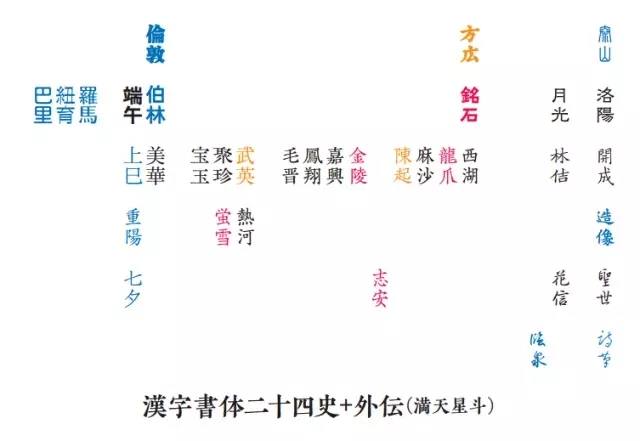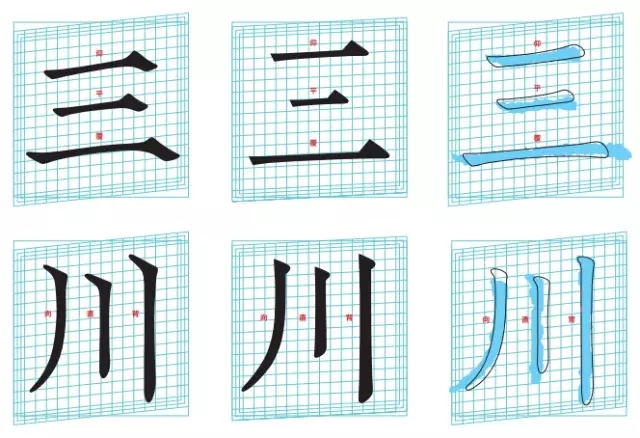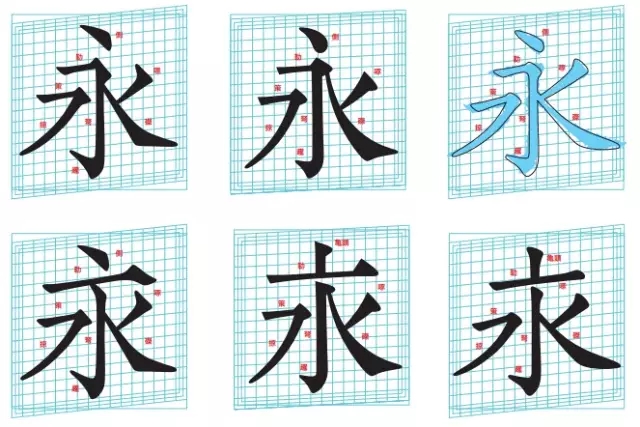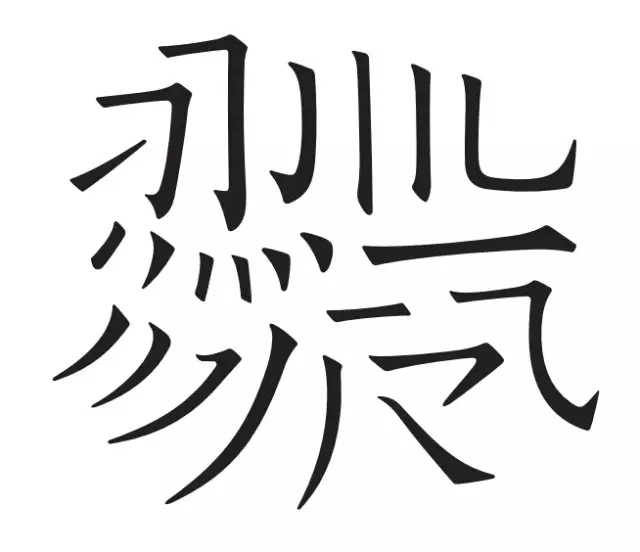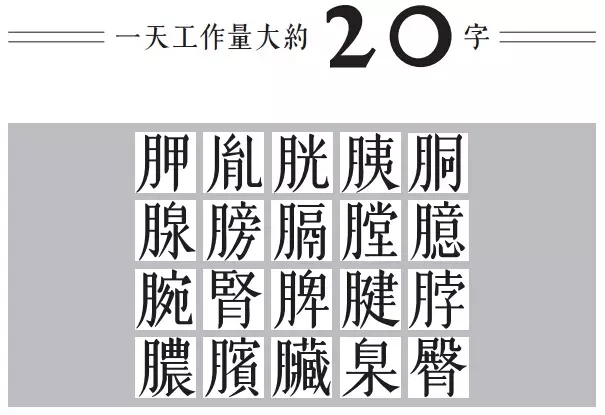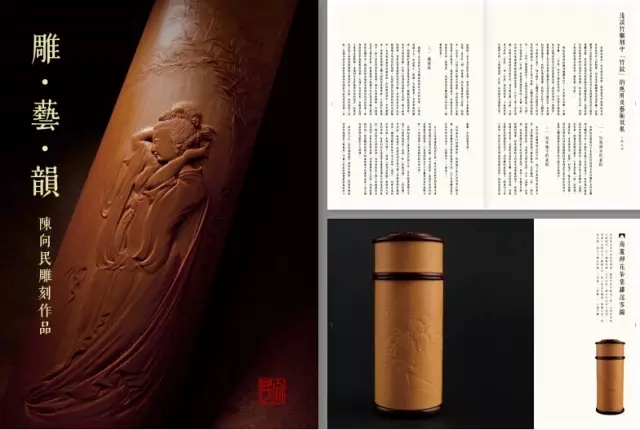
中文复刻字体研讨会
导语海报设计:杨林青1月9日下午2时,一场由北京北大方正电子有限公司(以下简称“方正电子”)与北京大学现代出版研究所合作主办的字体盛会——“中文复刻字体研讨会暨方正金陵粗、方正金陵细、方正龙爪、方正萤雪字体发布会”在北京大学百年纪念大讲堂隆重召开。300余名字体及设计爱好者齐聚一堂,与在场的对古籍文化和字体颇有研究的大咖们一起,近距离探讨了复刻字体的前世今生以及未来,并一同见证了方正金陵粗、方正金陵细、方正...
1月9日下午2时,一场由北京北大方正电子有限公司(以下简称“方正电子”)与北京大学现代出版研究所合作主办的字体盛会——“中文复刻字体研讨会暨方正金陵粗、方正金陵细、方正龙爪、方正萤雪字体发布会”在北京大学百年纪念大讲堂隆重召开。
300余名字体及设计爱好者齐聚一堂,与在场的对古籍文化和字体颇有研究的大咖们一起,近距离探讨了复刻字体的前世今生以及未来,并一同见证了方正金陵粗、方正金陵细、方正龙爪、方正萤雪四款复刻字体的发布。
以下是来自七位嘉宾(肖东发、今田欣一、汤婷、应永会、刘庆、姜寻、杨林青)以及学术主持仇寅的精彩分享,满满的都是干货哦~
主题演讲环节
肖东发
北京大学新闻与传播学院教授、北京大学现代出版研究所所长
演讲主题:《朝阳产业探寻规律——从出版史说起》
有人说出版是夕阳产业,我不赞成这个观点,如今我们讲的是大出版,它一定是个朝阳产业。因为有教育就得有出版,社会各行的发展,跟出版是互动前行的,只要人类存在,有信息传播,就有出版。回顾出版史我们不难得出很多有意义的结论。出版史有两个基础,其一就是文字要有语言为基础,因为文字是记录语言和传播的符号;其二,文字产生的基础是实物,没有实物也是不可能产生文字的。有文字的历史就是人类的文明史,这是第一个大的飞跃。再有一个飞跃,我觉得就是计算机光电技术。人类信息传播是一个动态的过程,从无到有,从简到繁,而科学技术的发展是整个推动力。为什么纸以前的媒介的都被淘汰了?我认为中外所有媒介的优势纸都具备,它又克服掉了它们的缺点。有人预言,未来是无纸的社会、计算机能够完全取代纸。我认为不可能,因为计算机不具备压倒优势,纸不受地方限制,我认为,纸永远不会消亡。为什么说出版是永远的?我的结论,出版是永恒的朝阳产业,它不仅是一个产业,它还有特殊的文化属性,关系到人类灵魂的升华。传统出版也不会消亡,就像纸业不会消亡一样。人们不能光网上看书,这叫浅阅读、快阅读,要想慢阅读、深阅读还得看书本。当然它俩不是矛盾的,新技术给出版如虎添翼;此外,不管是传统出版还是数字出版都离不开字体。我最后的结论是,理想和责任是出版人永远不变的人文情怀,融合与创新是出版永远的主旋律。
今田欣一
日本著名字体设计师、欣喜堂字体公司负责人
演讲主题:《温故知新》
2012年和方正电子一起合作的金陵、龙爪和萤雪终于可以发布了。现在我给大家展示一下“汉字书体二十四史+外传”,日语的书体就是字体,黑色的、橘色的和红色的加起来就是二十四史,蓝色的没有放到“二十四史”里面,只做了一些实验,所以补在后面,叫“外传”(满天星斗)。
右边这一块主要是手写系的字体。最右边一列是以石碑文字为基础做出来的,从上到下分别是篆书、隶书、楷书、北魏的石碑、行书和草书,出自《熹平石经》的洛阳、出自《开成石经》的开成,出自王羲之行书的圣世,出自怀素草书的诗草。第二列是从刊本选出来的,隶书体的月光、楷书体的林佶和行书体的花信。底下的叫临泉,是日本特有的。左边的端午、上巳、重阳、七夕是现代排印的活字字体,分别是黑体、宋体、楷书和仿宋,端午是从人民文学出版社的字样中抠出来做的,上巳是从商务印书馆的刊物中抠出来的,重阳是汉文正楷书局的,七夕则是中华书局,这四款是从中国的出版社做的中国活字中复刻出来的。从最右边的书法手写体到左边的印刷字体,中间的这部分是我所研究的“二十四史”的最关键的一个系列。我给它们分成了几个区,我给每个区起的名字可能和中国朋友起的名字不一样。西湖、龙爪、麻沙、陈起是宋朝体,志安是元朝体,金陵、嘉兴、凤翔、毛晋是明朝体,热河、萤雪是从清朝刻本出来的,我管它们叫清朝体,武英、聚珍、宝玉是过渡期明朝体,美华是近代明朝体。
接下来要说说这些刻本字体,我是怎么选的。北宋刻本,完全继承了唐朝的风格,保留的非常多,到了南宋以后,印刷的三大出版地是浙江、四川和福建,所以我在复刻宋朝字体的时候主要是从三大刻本出版地里找的。龙爪,我是选的四川刻本做出来的,方正龙爪体的原形就在这里。麻沙是福建刻本的字体,据说福建刻本是以柳公权的笔法为主。西湖、陈起是浙江刻本。志安是元朝体,它的书体风格和赵孟頫的笔法是很接近的。在复刻明朝体的时候,我是按出版社来选的刻本,金陵出自南京的国子监,嘉兴是佛教的刻本,凤翔选的是《乐律全书》郑藩刻本,毛晋选自非常有名的《毛晋汲古阁》刊本,它书法的笔法保留的比较多。后面的清朝刻本字体,是怎么选的呢?热河选自《御製文集》,比较有设计造型,据说是康熙帝比较喜欢,这个刻本返回楷书的笔法比较多一点。萤雪是选自扬州诗局的《钦定全唐文》刻本,也是官刻本。再说到过渡期的明朝体,武英是选自武英殿的《古今图书集成》,聚珍源自武英殿聚珍版,是木活字,宝玉则是出自民间出版的红楼梦,也是用木活字印出来的。虽然木活字看起来好像比较粗糙,有些参差不齐,但把断开的笔划再复原以后其实整个字的造型还是非常有意思的。铭石看起来是隶书,但做起来很有黑体的味道。方广和日本的古董体接近,是佛经佛刻的经典体。
刚才给大家介绍的这些字体并不是某一天冒出来的,而是有很长的历史渊源继承下来的。一边是书写书法,另一边是现代印刷的字体排印,其实中间有刻字或者美术字的过渡。现在的字体排印也是继承了原来的书法,经过刻字的总结以后才到现在的字体排印,同时,现在的字体排印也需要中间美术字造型的总结。在西文里,有各种各样的字体,还不断进行着复刻,同样一款字会有不同的厂商进行不同的复刻。而我们的汉字字体,其实历史比西文要长的多,所以我希望通过利用这么多的资源,把这些传统的字体都复刻出来。
前面讲的是历史的问题,下面给大家介绍一下我在复刻字体的时候,在设计方面怎么做的。
图中蓝颜色的就是原版的字。在书法中叫双勾填墨法,把轮廓给描出来。还有另外一种方法是临书,在临帖的时候一开始要模仿笔法和笔意,到后来就用自己的办法把它写出来。复刻正如临书一样,如果单纯的刻划勾原来的字的话,你只能写原来的字,不会写新的字。
复刻字体在制作过程中主要是在以下这几个方面不断的注意然后再进行发展:
首先是“十字二法”,就是一横一竖的写法,同样的一横一竖都会有起笔、送笔、收笔的不同。之后就是“三字三法”,就是说同样的横和竖在不同的位置上也会有不同的形状。后面就发展到了“永字八法”,永字八法的是指“侧、勒、弩、趯、策、掠、啄、磔”八划的笔法,永字八法包含了书法里很多字体的写法,还是要仔细的去分析。
笔法还有很多,我都分别起了名字。
汉字其实是很有层次感的,一开始先从笔法开始,笔法完了以后再组合起来变成部首,之后再组成一个字,是有层次的。
笔法介绍完了,然后是结法。虽然汉字是方块字,但也有菱形的、圆形的。关于结法,我写了“结法36法”。(详图见今田欣一讲义)
笔法、结法之后再做整个字的统一性和变化,在不断的分析和研究过程中,把这个字做出来。
最后是字距的问题,上图左边是宋朝的,中间是明朝的,右边是清朝,随着发展字越来越大,在宋朝的时候特别的拥挤。这不仅有字体的问题,还有排版的问题,要综合考虑。
在研究活字字体做法的时候,以笔法、结法和章法为三个中心,但是,复刻字体并不是单纯为了活字研究,更重要的是要让大家能够使用。在做字体的时候,字体设计师要考虑到自己做出来的字会被怎样使用。
下面给大家介绍一下龙爪、金陵、萤雪这三款日文字体在日本是怎么使用的。
这些活字字体大家可用做标题,其实排成正文也是很合适的。像金陵和龙爪,排成正文都非常好。我再补充一点,日本小说绝大部分是竖排,其实不仅是竖排,横排也可以用。
西文有很多字体,而汉字也是有很多字体资源的,我们有这么多的刻本资源,把一些活字字体开发出来,让出版有更多正文的表情,不是更好的事情吗?!无论是汉字字体还是西文字体,都是世界共通的文化遗产。作为设计师来讲,不能因为这是我设计的,就要去局限人家的使用。我作为字体设计师,我做出这些字体并不会把它当成我个人的作品,我更希望有更多的人来使用我的字体,希望我们以后能有更多的角度、更广的领域来合作。
汤婷
方正电子字体设计师、方正宋刻本秀楷体设计者
演讲主题:《中文复刻字体设计过程介绍》
方正设计开发的复刻字体,除了今天发布的方正金陵粗、方正金陵细、方正龙爪、方正萤雪,还有方正宋刻本秀楷、方正清刻本悦宋、方正润扁宋、方正聚珍新仿,我本人参与设计的是方正宋刻本秀楷。方正宋刻本秀楷是依照中国文物出版社出版的《毛主席诗词三十七首》与《攻媿先生文集》中的字形设计而来的。因为《攻媿先生文集》当时是由21个刻工刻的,所以在风格上有不统一的地方。我在设计的时候,首先从笔形着手,笔形首先从横划着手,先后取了“暖”、“泣”、“詠”、“乾”、“征”、“土”6个字进行勾字,最后把所有勾完的横划进行总结、规范,以便在之后拼字的时候起到借鉴作用;再用同样的方法把八大基础笔划的规范都制作出来了。当所有规范笔划都制作出来之后就进入试做阶段。以“土”字为例,勾完之后感觉重心不够平稳,于是我对字的结构做了适当的调整,将上横上移,下横右移。
宋刻本秀楷的八大基础笔划
“土”字最终效果跟原字效果的对比
《毛主席诗词三十七首》所有的字都按照以上的方法勾了,总共是974个汉字。974个汉字勾完之后还需要做相应的调整,主要是针对现在的排版方式,对字面、结构做调整。974个字并不能满足现今字库的规范要求,还有很多字是缺失的,这个时候我们就需要去拼字。拼字就是依照先前的974个字,从中选取需要的偏旁部首把它们拼成缺失的字。拼字并没有想象中那么简单,首先要控制单字的重心、字面与笔划粗细,提高字体的可读性。同时,为了保留雕版字体的手工痕迹,宋刻本秀楷没有像其他的字库一样,把所有的偏旁部首都做成一致。以“口”字为例,这7个字中所有的“口”字上都是不太一样的,就是为了保留雕版字的手工痕迹。
最终完成简体是7156个汉字,繁体包括6866个汉字,其中简体跟繁体共用的字形有4685。清刻本悦宋、润扁宋、聚珍新仿(还在制作中)在做的时候也大同小异。
接下来我介绍一下这次发布的四款复刻字体方正的设计过程,以金陵细和金陵粗为例。这四款字体都有简体和繁体,网上有人吐槽说繁体用起来不是非常方便,这次方正把简体和繁体合成一个字库。方正金陵首先是取的欣喜堂原版的字,根据我们的理解、根据国内的审美,统一调整了单字的布白与字面大小。
以“的”为例,欣喜堂金陵细的“白”跟“勺”大小的对比很明显,方正版的把“白”适当变大,“勺”适当调小。代表的“代”,方正把卧勾调小了。“在”字主要调整了重心,通过移动笔划调整角度、位置去改变整个字的字型。“梁”字与“光”字一样,都是把上边的部件变大,下面的部件变小。“著”将上、中、下三个部件的重心调整的比较对齐一些。方正版的“元”字跟“梁”、“光”一样,也是上边的部件变大,下边的“儿”变小了一些。
第四点,文字,特别是雕版文字,我深刻的感受有四个文化在深深的影响着它。一个是地域文化,南宋时期的三个刻本聚集之地,四川是颜体,福建是柳体,浙江是欧体。还有一个很重要的是师徒文化,中国的雕版都是师傅带徒弟,一个大师傅带好几个徒弟,也更容易形成地域文化。第三个是工具文化,我们的工具在变,原来是刻刀、毛笔,现在是鼠标,这些都会留下相应的痕迹。第四个是时代文化,每一款字体都会以某一个书法家的创作为基础,为什么宋体字最主流的以颜体字为主要依据,是因为颜真卿在宋朝得到了充分的肯定,他的人格魅力、影响力影响着这个时代,到了明清的时候风格又变了,这说明一种时代的文化会深刻的烙印在字体当中。拂去历史的尘埃,我们再来看这个事情,才会看的更明白。我们现在要做的事情就是尽我们的最大能力不断地创作更好的字体。